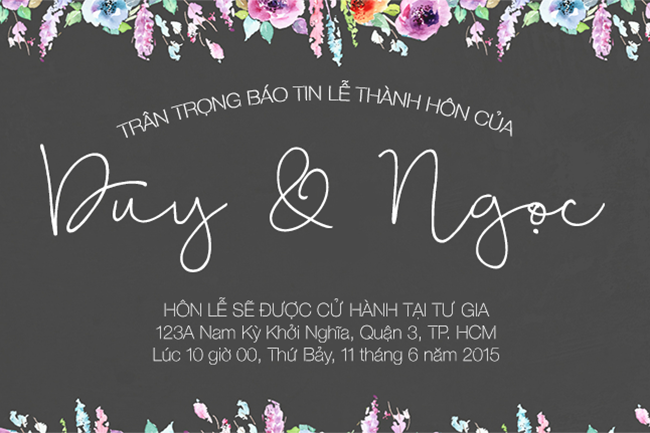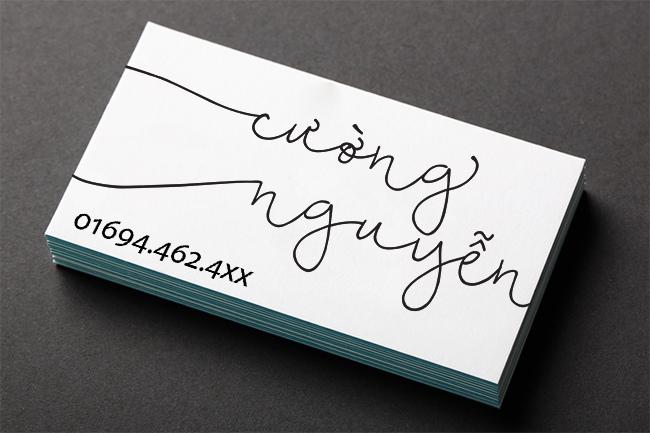
Gặp gỡ Bellwethers… một typeface vẽ tay cầu kỳ, mang phong cách doodle với vô số swash. Hoàn hảo để thêm chút tinh nghịch và vẻ thanh lịch phóng khoáng cho dự án tiếp theo của bạn.
Nhà thiết kế: Angie Makes